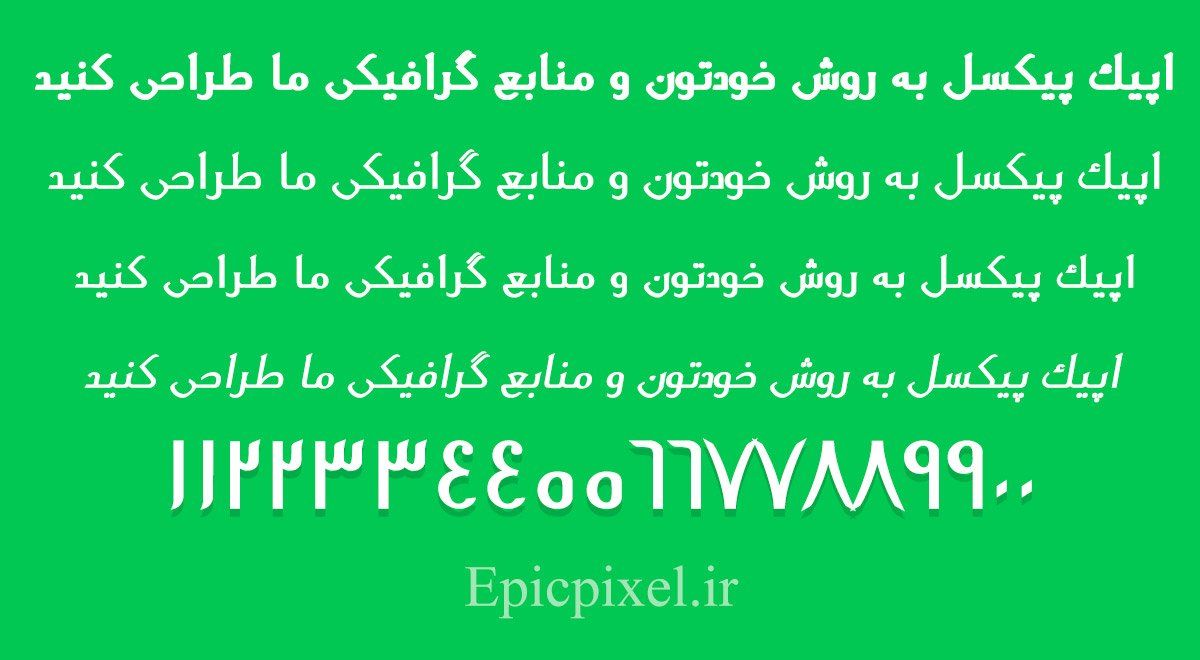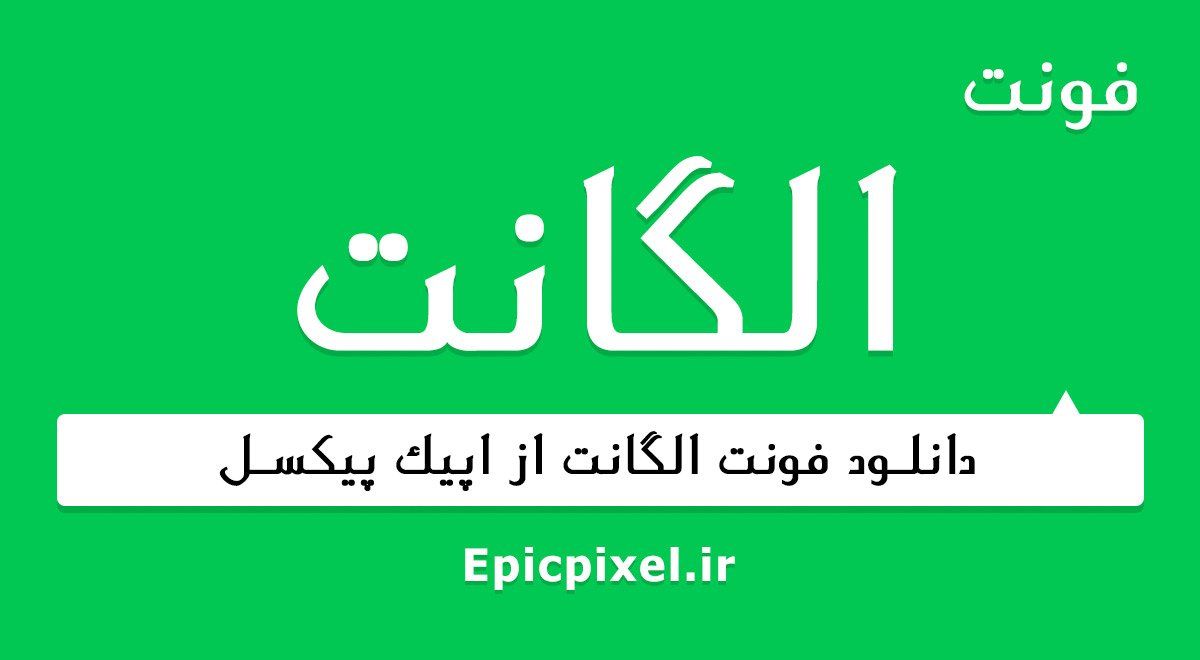
6 فونت الگانت فارسی Elegant
اگر به دنبال فونت الگانت فارسی برای پروژه های طراحی خود هستید، مجموعه هایی مانند Mj Elegant Bold و Mj Elegant Light گزینه های ایده آلی هستند. این فونت ها با خطوط تمیز و ظریف، حرفه ای ترین نتایج را برای لوگو، مجلات، و برندینگ ایجاد می کنند. همچنین، مجموعه ۶ فونت الگانت فارسی از اپیک پیکسل شامل تنوعی از استایل های ضخیم و لایت است که انعطاف پذیری را در طراحی های دیجیتال افزایش می دهد.
برای علاقه مندان به ظاهر لوکس، فونت رونالتو با طراحی سریف و مدرن، انتخابی عالی برای مجلات و بسته بندی محصولات است . این مجموعه ها نه تنها کیفیت بالایی دارند، بلکه سازگاری کامل با نرم افزارهای گرافیکی مانند ایلاستریتور را نیز ارائه می دهند . استفاده از فونت الگانت فارسی در پروژه های گرافیکی، نه تنها حرفه ایسم شما را نشان می دهد، بلکه باعث جذب توجه مخاطبان می شود. این مجموعه ها شامل فونت های گرافیکی با جزئیات پیچیده هستند که برای لوگو و تایپوگرافی مناسبند.
با دانلود این فونت ها، هر طرحی را به یک اثر هنری تبدیل کنید و از تنوع استایل های آن ها برای ایجاد تفاوت در پروژه های خود استفاده کنید.